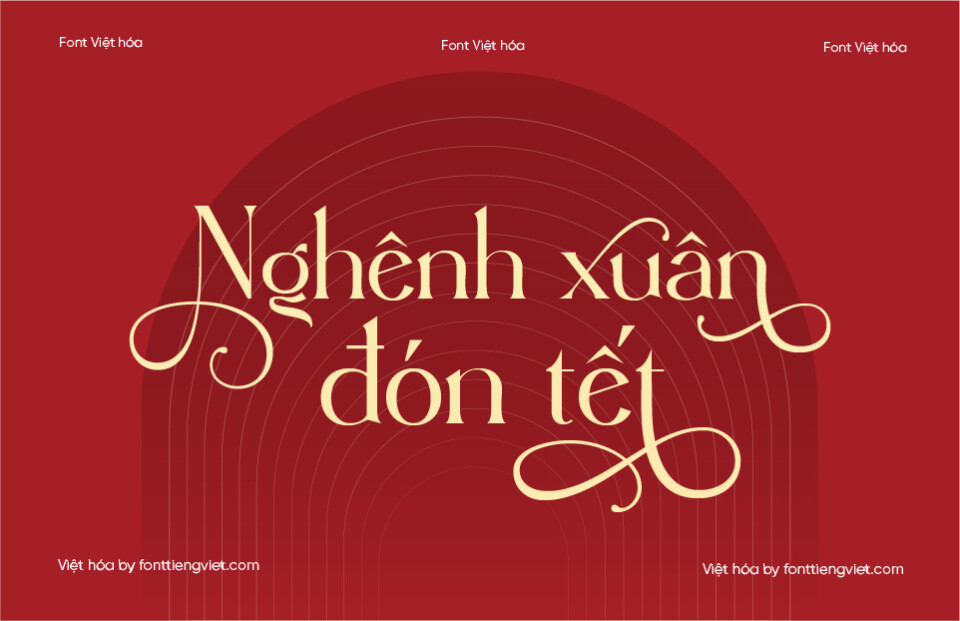
Font Việt hóa 1FTV VIP Angrela Display – Tết
Font Việt hóa 1FTV VIP Angrela Display – Tết Sang Trọng Và Đẳng Cấp Cho Thiết Kế Chúc Mừng Năm Mới
Giới thiệu về Font Việt hóa 1FTV VIP Angrela Display – Tết
Trong không khí rộn ràng của những ngày cuối năm, việc tìm kiếm một bộ Font Miễn Phí chất lượng để thiết kế bao lì xì, thiệp chúc mừng hay banner sự kiện là vô cùng quan trọng. Font Việt hóa 1FTV VIP Angrela Display – Tết chính là lựa chọn hoàn hảo dành cho các nhà thiết kế chuyên nghiệp lẫn các bạn học sinh đang tập tành làm đồ họa. Đây là bộ font chữ sở hữu đường nét thanh mảnh nhưng vẫn giữ được sự mạnh mẽ, mang đậm hơi thở hiện đại xen lẫn nét truyền thống Á Đông.
Đặc điểm nổi bật của Font Việt hóa 1FTV VIP Angrela Display – Tết
Bộ font này được tối ưu hóa hoàn toàn cho tiếng Việt với các dấu thanh được đặt đúng vị trí, giúp văn bản không bị lỗi hiển thị khi đánh máy. Điểm đặc biệt của Font Việt hóa 1FTV VIP Angrela Display – Tết nằm ở các chi tiết uốn lượn nghệ thuật, tạo nên sự sang trọng và tinh tế cho các tiêu đề lớn. Với định dạng Display, font chữ này cực kỳ phù hợp để làm điểm nhấn cho các ấn phẩm in ấn quảng cáo dịp Tết Nguyên Đán sắp tới.
Ứng dụng thực tế và cách sử dụng hiệu quả
Bạn có thể sử dụng font chữ này cho nhiều mục đích khác nhau như thiết kế poster sự kiện trường học, trang trí bảng tin lớp hay làm phụ đề cho các video mừng Xuân. Để phát huy tối đa vẻ đẹp của font, bạn nên kết hợp với các tông màu đỏ, vàng hoặc nhũ bạc. Việc sử dụng các biến thể chữ hoa trong bộ Font Việt hóa 1FTV VIP Angrela Display – Tết sẽ giúp thông điệp của bạn trở nên nổi bật và thu hút ánh nhìn ngay từ giây phút đầu tiên.
Kết luận về bộ font chữ cao cấp này